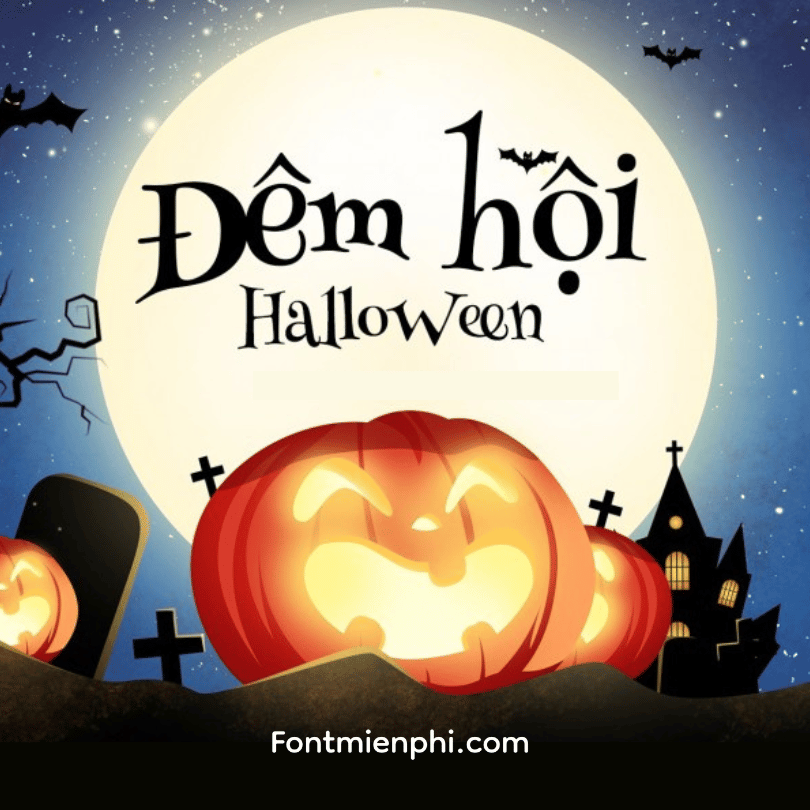
Việt hóa font 1FTV Henny Penny phong cách Halloween – Phông Chữ Halloween Vui Nhộn & Độc Đáo
1FTV Henny Penny là font chữ Việt hóa với phong cách Halloween vui tươi, kỳ quặc nhưng cực kỳ cuốn hút. Lấy cảm hứng từ những nhân vật hoạt hình dị biệt, font chữ này mang đến không khí lễ hội vừa đáng yêu vừa có chút ma mị.
ĐẶC ĐIỂM NỔI BẬT:
✔ Hỗ trợ đầy đủ tiếng Việt (Unicode) – dễ dàng sử dụng cho mọi dự án
✔ Phong cách chữ “kỳ dị nhưng dễ thương” – nét tròn trịa biến hóa, phù hợp thiết kế Halloween cho trẻ em
ỨNG DỤNG HOÀN HẢO:
- Thiết kế áo thun, sticker Halloween vui nhộn
- Poster tiệc Halloween gia đình
- Banner quảng cáo kẹo Halloween
- Thiệp mời lễ hội hóa trang